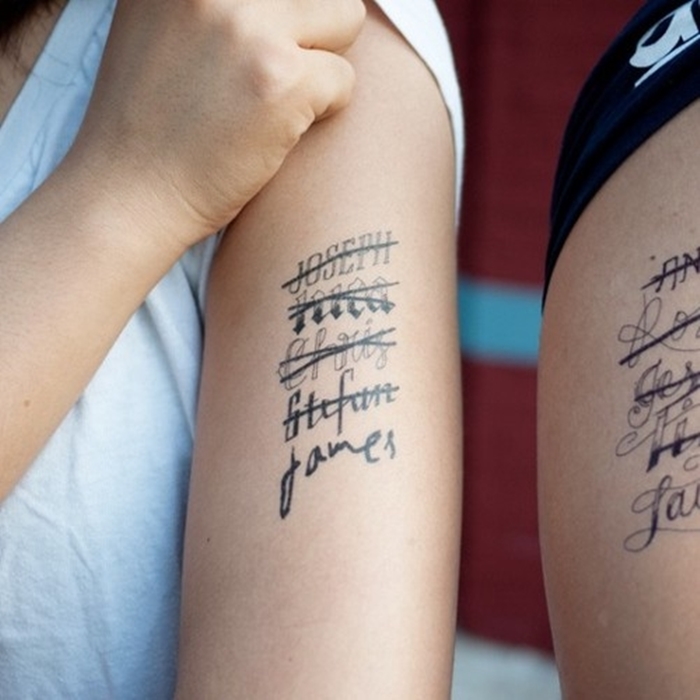
Иметь татуировку на своем теле сейчас считается модным. Особенно здорово, если нательное изображение несет в себе определенный смысл. Татуировка в виде надписи может стать отличным мотиватором для вас и окружающих. Татуировки-тексты могут выполняться различными стилями: от элегантного прописного до минималистического печатного. Рисунки со словами или цитатами лучше других раскрывают сущность человека, напоминая о том, через какие испытания пришлось пройти или о счастливых моментах жизни.
К тому же татуировки в виде надписей хороши и тем, что вряд ли вы встретите человека с подобным изображением. Вы можете проявить свою индивидуальность посредством текста. Кстати и здесь вам представляется выбор, вы можете написать слова как на родном языке, так и на иностранном. Одно из самых популярных мест нанесения такой тату — рука. Об этом читайте подробнее с посте «Татуировка на руках: надписи с переводом (фото) », а также «Текст тату: перевод с английского (фото) „.
Татуировки надписи с переводом
Татуировки на латыни с переводом
Лидирующее место среди иноязычных источников занимают английский и латынь. Однако китайские и японские надписи-иероглифы также пользуются большим спросом. Стоит отметить, что татуировки с латинским текстом часто выражают философский смысл, так как они, как правило, были изречениями знатных и великих людей античности. Латинские цитаты можно увидеть как на мужчинах, так и на женщинах.
Все знают, что Анджелина Джоли большая поклонница нательных изображений.
Самой известной татуировкой актрисы считалась надпись с именем бывшего мужа Билли Боба Торнтона „Billy Bob“, от которой позднее звезда решила избавиться. Теперь все внимание приковано к кресту и надписи по латыни “ Quod me netrit me destruit» внизу живота Анджелины. Эти татуировки актриса сделала в Амстердаме, находясь в алкогольном опьянении. Может быть, поэтому звезда кинематографа остановила свой выбор на такой глубокой фразе «Что меня питает, то и убивает»?
Дэвид Бекхэм разделил свою страсть к татуировкам уже давно. Очевидно, что надписи являются любимым видом нательных рисунков для спортсмена. Имена четверых детей и любимой жены Виктории запечатлены на шее и руках Дэвида. Для того чтобы объединить всю семью вместе звезда футбола нанес себе кельтский текст на внутренней стороне предплечья » Ut Amem Et Foveam«, означающий «Это то, что я люблю и боготворю». Другие татуировки на латыни не менее красивы и значимы. mixfacts. ru выбрал для вас самые яркие и запоминающиеся татуировки с переводом.
Татуировки надписи с переводом: Aut Viam Inveniam Faciam — Или я найду путь, или сам его проложу
Татуировки надписи с переводом: Tempus neminet ment — Время никого не ждет
Татуировки надписи с переводом: illicitus — запретный
Татуировки надписи с переводом: Alis Volat Propiis — летит на собственных крыльях
Татуировки надписи с переводом: Ad Astra Per Aspera — Через тернии к звездам
Фразы на латинском языке с переводом:
Amor Vincit Omnia (любовь побеждает все) Morior invictus (лучше умереть, чем быть побежденным) Amor et honor (любовь и честь) Vincit qui se vincit (самая трудная победа — это победа над собой) Faber est quisque fortunae suae (человек сам творец своей судьбы) Esto quod es (будь тем, кем ты есть на самом деле) Ut Amem Et Foveam (это то, что я люблю и боготворю) Verba volant, scripta manent (слова улетают, написанное остается) Luctor et emergo (я борюсь, но я выживу) Veritas vos liberabit (правда освободит тебя) Vita est speciosa (жизнь прекрасна) Vivere in momento (жизнь состоит из моментов) Minima maxima sunt (самые маленькие вещи являются самыми важными в жизни) Quis Attero Mihi Tantum Planto Mihi Validus (что меня не убивает, то делает меня сильнее) Si vis amari ama (если хочешь, чтобы тебя любили, люби сам) Veritas lux mea (правда — это свет в моей жизни) Vive ut vivas (жизнь такая, какой ты ее делаешь) Ab altero expectes, alteri quod feceris (Жди от другого того, что сам ты сделал другому) Aetate fruere, mobili cursu fugit (Пользуйся жизнью, она так быстротечна) Actum ne agas (С чем покончено, к тому не возвращайся) Amicos res secundae parant, adversae probant (Друзей создаeт счастье, несчастье испытывает их) Amor, ut lacrima, ab oculo oritur, in cor cadit (Любовь, как слеза, из глаз рождается, на сердце падает) Audire ignoti quom imperant soleo non auscultare (Послушать глупость я готов, а слушаться не буду) Aut vincere, aut mori (Или побеждать или умирать) Carpe diem (Лови момент) Certum voto pete finem (Ставь себе лишь достижимые цели) Consultor homini tempus utilissimus (Время — самый полезный советчик человеку) Damant, quod non intelegunt (Осуждают, потому что не понимают) Ducunt volentem fata, nolentem trahunt (Желающего идти судьба ведет, нежелающего влачит) Dura lex, sed lex (Суров закон, но это закон) Dum spiro, amo atque credo (Пока дышу, люблю и верю) Esse oportet ut vivas, non vivere ut edas (Надо есть, чтобы жить, а не жить, чтобы есть) Esse quam videri (Быть, а не казаться) Etiam innocentes cogit mentiri dolor (Боль заставляет лгать даже невинных) Ex nihilo nihil fit (Из ничего ничто не происходит) Experientia est optima magistra (Опыт лучший учитель) Facta sunt potentiora verbis (Поступки сильнее слов) Felix, qui quod amat, defendere fortiter audet (Счастлив, кто смело берет под свою защиту то, что любит) Fidelis et forfis (Верный и смелый) Finis vitae, sed non amoris (Кончается жизнь, но не любовь) Fors omnia versas (Слепой случай меняет все) Fortes fortuna adjuvat (Смелым судьба помогает) Fortunam citius reperis, quam retineas (Счастье легче найти, чем сохранить) Fortunam suam quisque parat (Свою судьбу каждый находит сам) Fugit irrevocabile tempus (Бежит невозвратное время) Gustus legibus non subiacet (Вкус не подчиняется законам) Gutta cavat lapidem (Капля точит камень) Homines quo plura habent, eo cupiunt ampliora (Чем больше люди имеют, тем больше желают иметь) Homo hominis amicus est (Человек человеку друг) Homo sum et nihil humani a me alienum puto (Я человек, и ничто человеческое мне не чуждо) Ibi potest valere populus, ubi leges valent (Там, где законы в силе, и народ силен) Ignoscito saepe alteri, nunquam tibi (Другим прощай часто, себе никогда) Imago animi vultus est (Лицо — зеркало души) Imperare sibi maximum imperium est (Повелевать собою — величайшая власть) In dubio abstine (При сомнении воздерживайся) Incertus animus dimidium sapientiae est (Сомнение — половина мудрости Memento quod es homo (Помни, что ты человек) Me quoque fata regunt (Я тоже подчиняюсь року) Mortem effugere nemo potest (Смерти никто не избежит) Ne cede malis (Не падай духом в несчастье) Potius sero quam nunquam (Лучше поздно, чем никогда) Procul negotiis (Прочь неприятности) Qui sine peccato est (Кто без греха) Suum cuique (Каждому свое) Trahit sua quemque voluptas (Каждого влечет его страсть) Tu ne cede malis, sed contra audentior ito (Не покоряйся беде, но смело иди ей навстречу) Unam in armis salutem (Единственное спасение — в борьбе) Vale et me ama (Прощай и люби меня) Vita sene libertate nlhil (Жизнь без свободы — ничто) Audaces fortuna juvat (смелым судьба помогает) Bene vobis (пусть все будет хорошо) Cantica gignit amor (любовь рождает песни) Capiat qui capere potest (лови, кто может поймать) Contra spem spero (надеюсь вопреки ожиданию) Cuivis dolori remedeum est patientia (от всякой боли средство есть — терпение) Cupido atque ira consultores pessimi (страсть и гнев — наихудшие советчики) Debes, ergo potes (должен, значит можешь) Ego me non fallo (я не ошибся.
Я твердо утверждаю) Est dolendi modus, non est timendi (для печали есть предел, для страха нет) Exceptio regulum probat (исключение подтверждает правило) Felix, qui potuit rerum cognoscere causas (счастлив тот, кто мог познать причины вещей) Fiat justitia, ruat caelum (пусть вопреки всему торжествует правосудие) Fide, sed cui fidas, vide (будь бдительным; доверяй, но смотри, кому доверяешь) Fortunam suam quisque parat (свою судьбу каждый находит сам) Gutta cavat lapidem (капля точит камень) Homines non odi, sed ejus vitia (не человека ненавижу, а его пороки) Magna et veritas, et praevalebit (Нет ничего превыше истины, и она восторжествует) Meliora spero (Надеюсь на лучшее) Melioribus utire fatis (Пусть счастливая судьба твоя будет) Nihil sine labore (Ничто не даётся без труда) Nil de nihito fil (Ничто не возникает из ничего) Nil desperandum (Не надо отчаиваться) Nil inultum remanebit (Ничто не остается безнаказанным) Nil permanent sub sole (Ничто не вечно под солнцем) Nolite judicare et non judicabimine (Не судите, да не судимы будите) Nomen est omen (Имя говорит само за себя) Non est ad astra mollis e terris via (Не гладок путь от земли к
звездам) Non licet in bello bis peccare (На войне ошибаются только раз) Non omnia passum omnes (Не всякий все может) Non omnia possumus (Не на все мы способны) Non omnis error stultitia est (Не всякая ошибка — глупость) Non progredi est regredi (Не идти вперед — значит идти назад) Non solum oportet, sed etiam necessese est (Нельзя быть всем одновременно первыми) Omne vivum ex ovo (Все живое вышло из яйца) Opera et studio (Трудом и старанием) Oportet vivere (Надо жить) Paulatim summa petuntur (Вершины достигаются не сразу)
Самые удобные места
Татуировка на английском, в большинстве случаев, создана для привлечения внимания, это своеобразный способ общения с миром, возможность сказать ему самую важную мысль, часто крутящуюся на языке . Именно поэтому такие надписи обычно не принято прятать. Они предпочитают применять:
- на запястье, что касается в основном девушек;
- на руках мужчин вдоль локтевой или лучевой кости;
- на наружную поверхность стопы;
- на спине или шее, та часть, которую можно открыть с помощью футболки;
- на грудь или ключицы.